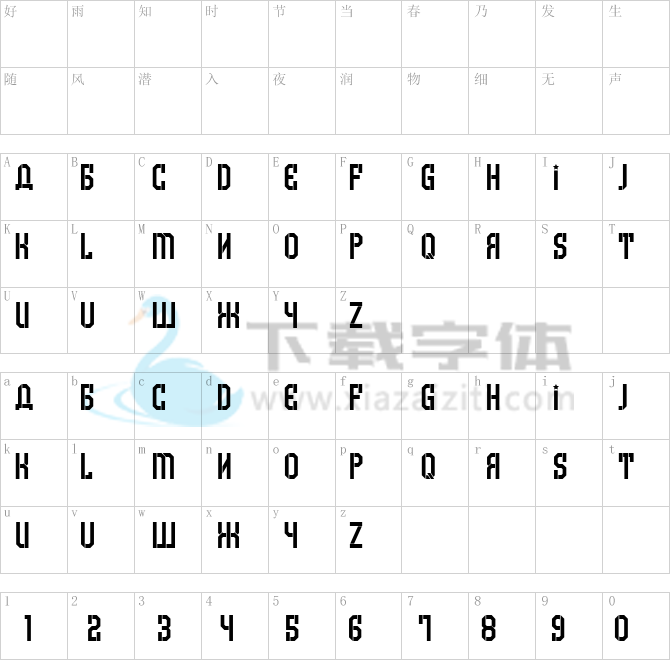
Armenia.ttf字体下载
Armenia.ttf字体下载,这款字体结构工整、笔画清晰,兼顾美观与易读性,适用于标题、正文、海报、包装、LOGO 等多种场景。字形优雅稳定,风格百搭耐看,适配日常排版与创意设计,让文字呈现更舒适、更具质感。Armenia.ttf字体下载一笔一画,皆是细节,以均衡的比例、流畅的线条打造舒适视觉体验,字形端正大气,风格简约现代。无论是商业设计、品牌宣传还是日常排版,都能轻松驾驭,让文字更有格调与力量。Armenia.ttf字体下载字体下载。
• 字体名称:Armenia
• 字体标识 ID:VladimirNikolic: Armenia Regular: 2017
• 字体全名:Armenia Regular